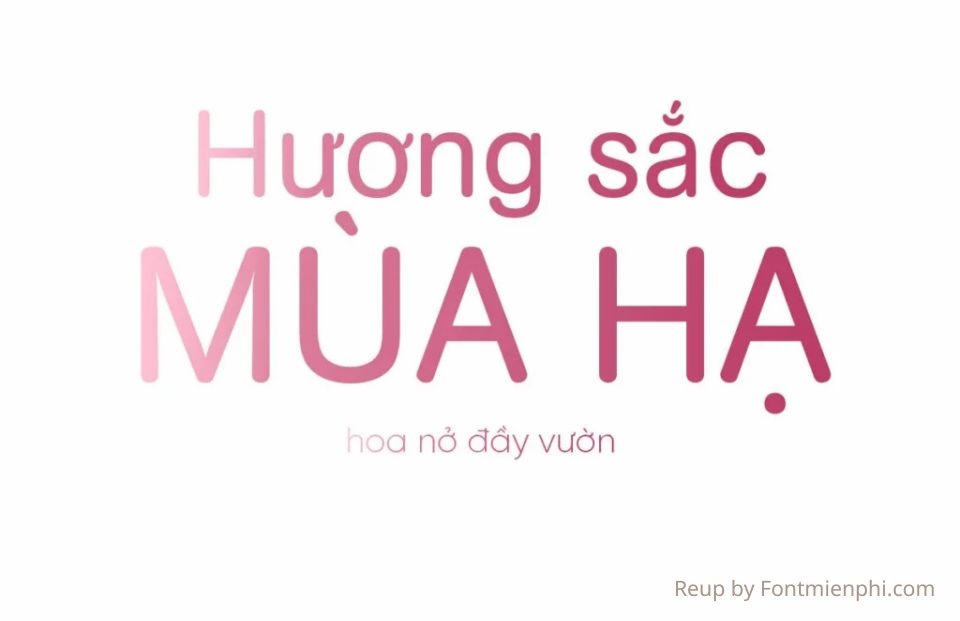
Trọn Bộ 2 Font VL AG Book Việt Hóa Miễn Phí
Fontmienphi.com Giới Thiệu: Trọn Bộ 2 Font VL AG Book Việt Hóa Miễn Phí – Giải Pháp Thiết Kế Hiện Đại
Nếu bạn đã quá nhàm chán với những kiểu chữ sans-serif (không chân) góc cạnh, cứng nhắc và đang tìm kiếm một làn gió mới mang tính thân thiện, hiện đại hơn, thì bộ đôi VL AG Book chính là sự lựa chọn không thể tuyệt vời hơn để nâng cấp các dự án sáng tạo của bạn.
🌟 Tổng Quan Về Trọn Bộ 2 Font VL AG Book Việt Hóa Miễn Phí
VL AG Book là một bộ phông chữ thuộc nhóm sans-serif (không chân) đã được Việt hóa chỉn chu, bao gồm 2 định dạng trọng lượng (weight) cực kỳ hữu dụng: Small (Nét mảnh) và Regular (Nét thường/đậm hơn).
Điểm đắt giá nhất của AG Book nằm ở chi tiết bo tròn mềm mại tại các góc chữ. Chính thiết kế tinh tế này đã phá vỡ sự khô khan thường thấy ở các font chữ không chân truyền thống, mang lại một tổng thể cực kỳ thân thiện, trẻ trung và hiện đại. Sự kết hợp hoàn hảo giữa phiên bản nét mảnh và nét đậm giúp bộ font giải quyết triệt để bài toán phân cấp thông tin (hierarchy) trong thiết kế, giúp nội dung vừa dễ đọc vừa toát lên vẻ chuyên nghiệp, tinh tế.
💎 Đặc Điểm Nổi Bật Của Trọn Bộ 2 Font VL AG Book Việt Hóa Miễn Phí
• Bộ đôi linh hoạt: Tích hợp sẵn 2 file font Small và Regular, giúp bạn dễ dàng tạo sự tương phản chữ (typography contrast) ấn tượng mà không cần tìm kiếm các font ghép nối khác.
• Thiết kế bo tròn tinh tế: Các đường nét sans-serif được xử lý bo góc mềm mại, tạo cảm giác thân thiện, an toàn và dễ gần cho người xem.
• Cân bằng thị giác hoàn hảo: Sự kết hợp nhịp nhàng giữa nét đậm và nét mảnh giúp bộ font hỗ trợ cực tốt cho mọi nhu cầu từ tiêu đề chính đến văn bản phụ.
• Việt hóa 100% chuẩn mực: Hỗ trợ đầy đủ bộ mã ký tự và hệ thống dấu tiếng Việt, loại bỏ hoàn toàn nỗi lo lỗi font khi gõ nội dung.
• Hiển thị xuất sắc đa kích thước: Cấu trúc chữ rõ ràng, mạch lạc giúp font giữ được độ sắc nét và tính dễ đọc dù ở kích thước banner khổng lồ hay trên màn hình điện thoại nhỏ hẹp.
🎨 Khả Năng Ứng Dụng Đa Dạng Trong Thiết Kế – Trọn Bộ 2 Font VL AG Book Việt Hóa Miễn Phí
Với sự đa năng và tính thẩm mỹ cao, 2 Font VL AG Book là “vũ khí” lý tưởng để bạn chinh phục nhiều hạng mục thiết kế khác nhau:
• Thiết kế quảng cáo & Social Media: Tạo ra các banner, ảnh bài đăng Facebook, Instagram mang phong cách trẻ trung, hiện đại và thu hút tương tác.
• Dàn trang ấn phẩm: Cực kỳ phù hợp để dàn trang catalogue, brochure, profile công ty nhờ khả năng phân bổ nội dung dễ đọc, chuyên nghiệp.
• In ấn truyền thông: Lựa chọn an toàn và hiệu quả cho các mẫu poster sự kiện, tờ rơi (flyer) quảng bá sản phẩm.
• Nhận diện thương hiệu (Branding): Phù hợp với các thương hiệu hướng tới sự tối giản, thân thiện như ngành công nghệ, giáo dục, F&B (đồ ăn/thức uống) hay các startup hiện đại.
• Typography tối giản (Minimalism): Tuyệt vời để ứng dụng trong các thiết kế đề cao không gian trống và nghệ thuật sắp đặt chữ.